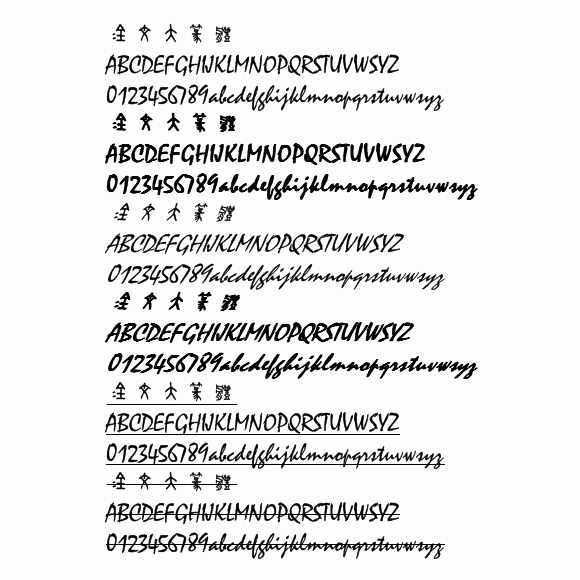
軟件介紹 軟件標簽: 金文大篆體 篆體 字體 金文大篆體字中相對與篆體粗細不勻的線條變得均勻柔和了,隨實物畫出的線條十分簡練生動,是在篆體中比較常見的,我們將該字體下載提供給您,歡迎您的下載使用。金文大篆體字體預覽金文大篆體字體安裝說明1、點擊打開金文大篆體字體,直接選擇安裝即可2、將字體復制到C:\Windows\Fonts文件夾即可完成安裝。注意事項本站所有字體資源僅供個人學習與參考,如需商業使用請到相關官網授權。 軟件截圖 上一張下一張(1 / 1) 安裝詳細截圖 猜你喜歡 篆書字體 篆書字體 篆書是最早的一種書體,這款字體有著中國悠久歷史的文化氣息,方筆、圓筆、尖筆是篆書的共同特點,從周代時期,篆書就開始形成雛形,隨著歷史的發展,篆書也在不斷變化,每個時期都有其自身的特色,現在的漢字就是有小篆演變而來。風格渾厚樸茂的篆書字體也受到廣發歷史研究者的喜愛,這里包含了篆書字體大全,有需要的朋友歡迎來綠色資源網下載體驗! 查看更多>> 手機篆體字 31.25M/中文/5.0/v3.1 安卓版下載 篆書查詢軟件 24.52M/中文/5.0/v7.5 安卓手機版下載 方圓印章篆體 2.44M/中文/6.6/下載 青銅器銘文字體 4.08M/中文/6.6/下載 富漢通粗印篆體繁字體 14.40M/中文/5.0/下載 fcuzuan(迷你繁篆書) 2.44M/中文/5.0/ttf免費版下載 其他版本下載 標題 大小 更新日期 下載 經典繁印篆體 1.76M 2019-05-30 下載 華康新篆體繁體字體 3.23M 2017-01-18 下載 篆體字體打包合集 50.82M 2019-01-05 下載 小篆字體轉換器(方正小篆體) 綠色版 2.54M 2015-05-09 下載 經典簡方篆體 890KB 2019-05-28 下載 漢儀小篆字體 ttf 2.47M 2019-06-06 下載 下載地址 電腦版 金文大篆體 ttf免費版 點擊報錯 軟件無法下載或下載后無法使用,請點擊報錯,謝謝! 關閉報錯反饋 請描述您所遇到的錯誤,我們將盡快予以修正,謝謝! *必填項,請輸入內容 本類最新 首爾南山體字體 v1.06 官方版 潮字社風云簡ttf 潮字社凌渡鯤鵬簡體字體 潮字社曾玉波手書簡字體 微博慧心字體 阿里巴巴iconfont字體庫 相關文章 Photoshop字體安裝使用方法和技巧 如何解決“無法新增字體”問題 Win 7系統安裝字體方法 網頁字體大小設置方法 怎么改網頁字體大小 在Linux系統中安裝字體的幾種方法 windows7字體顯示問題:打開某些程序的時候顯示的是亂碼 用戶評論 熱門評論 最新評論 發表評論 查看所有評論(0) 昵稱: 請不要評論無意義或臟話,我們所有評論會有人工審核. 字數: 0/500 (您的評論需要經過審核才能顯示)